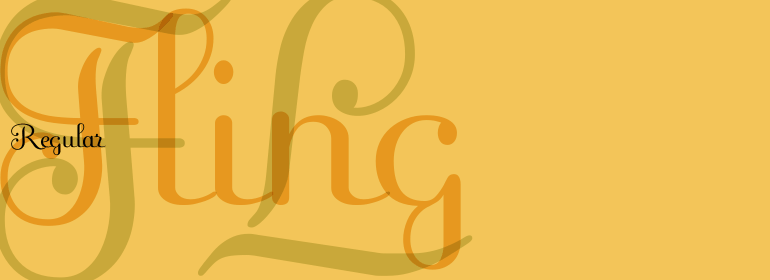
Fling™
Michael Gills曾任Letraset的常驻设计师,他于1995年创作了Fling字体。Fling的字形基于法国手写风格字体Ronde(或 Round)。该字体的大写字母复杂宽大,与比较保守的小写字母形成鲜明对比。这样就允许在文本中出现复杂和优雅的风格。
Fling的字形对于那些手写字体而言非常清晰,它用途广泛。除了少量的正在运行的文本,Fling的大写字母也可以作为首字母。在Opentype字体中有额外的连字和替代字形,可以提供各种扩展的排印可能。
Michael Gills, formerly a resident designer at Letraset, created the Fling typeface in 1995. Fling's letterforms are based on the Ronde--or round--script style from France. The design includes intricate and generous capital letters, which are contrasted with a more reserved lowercase letters. This allows for a sophisticated and elegant appearance in text.
Fling's letterforms are highly legible for those of a script face, and it is a typeface with many uses. Aside from short amounts of running text, Fling's capital letters serve well as initials. In the Opentype font are extra ligatures and alternative letterforms thatoffer expanded typesetting possibilities.